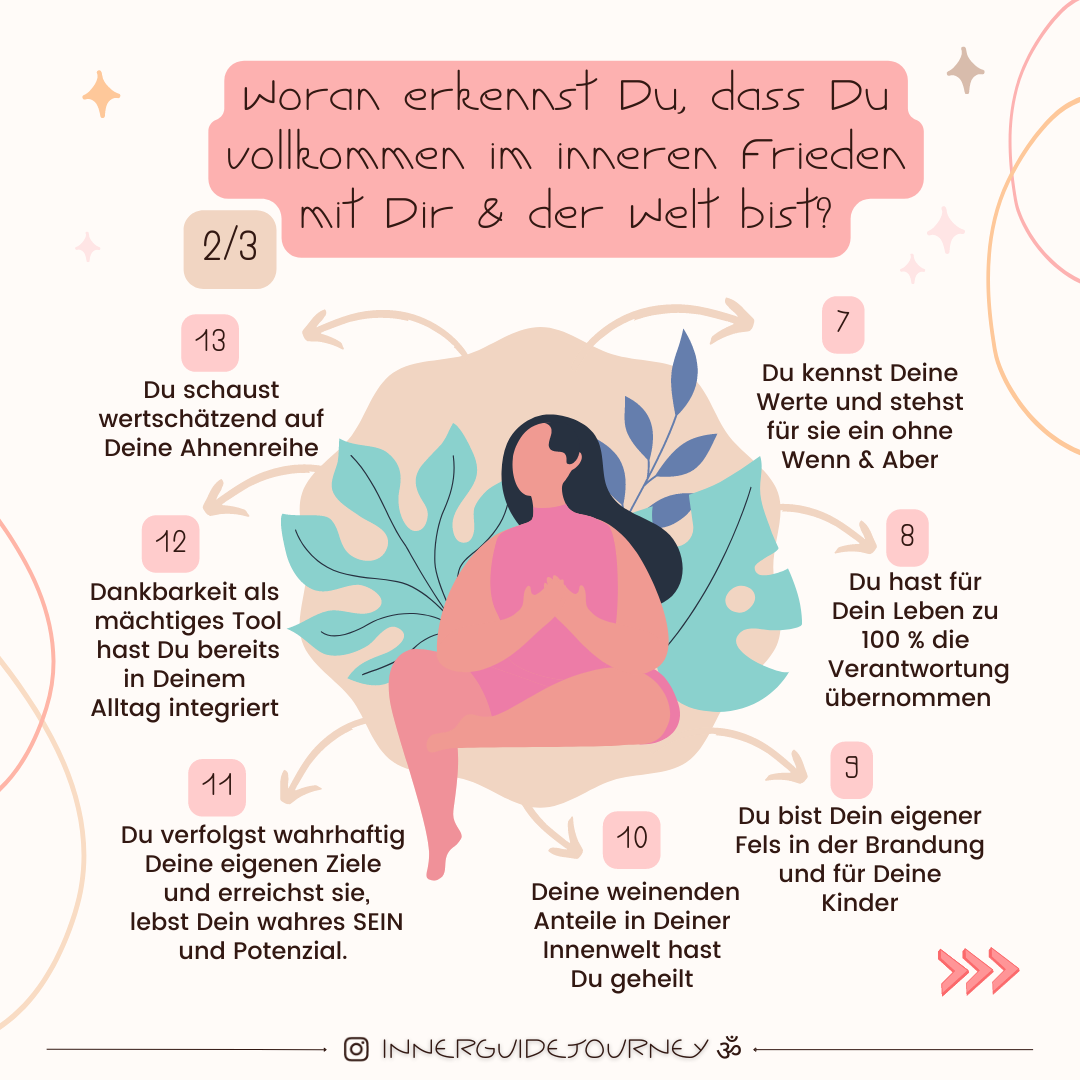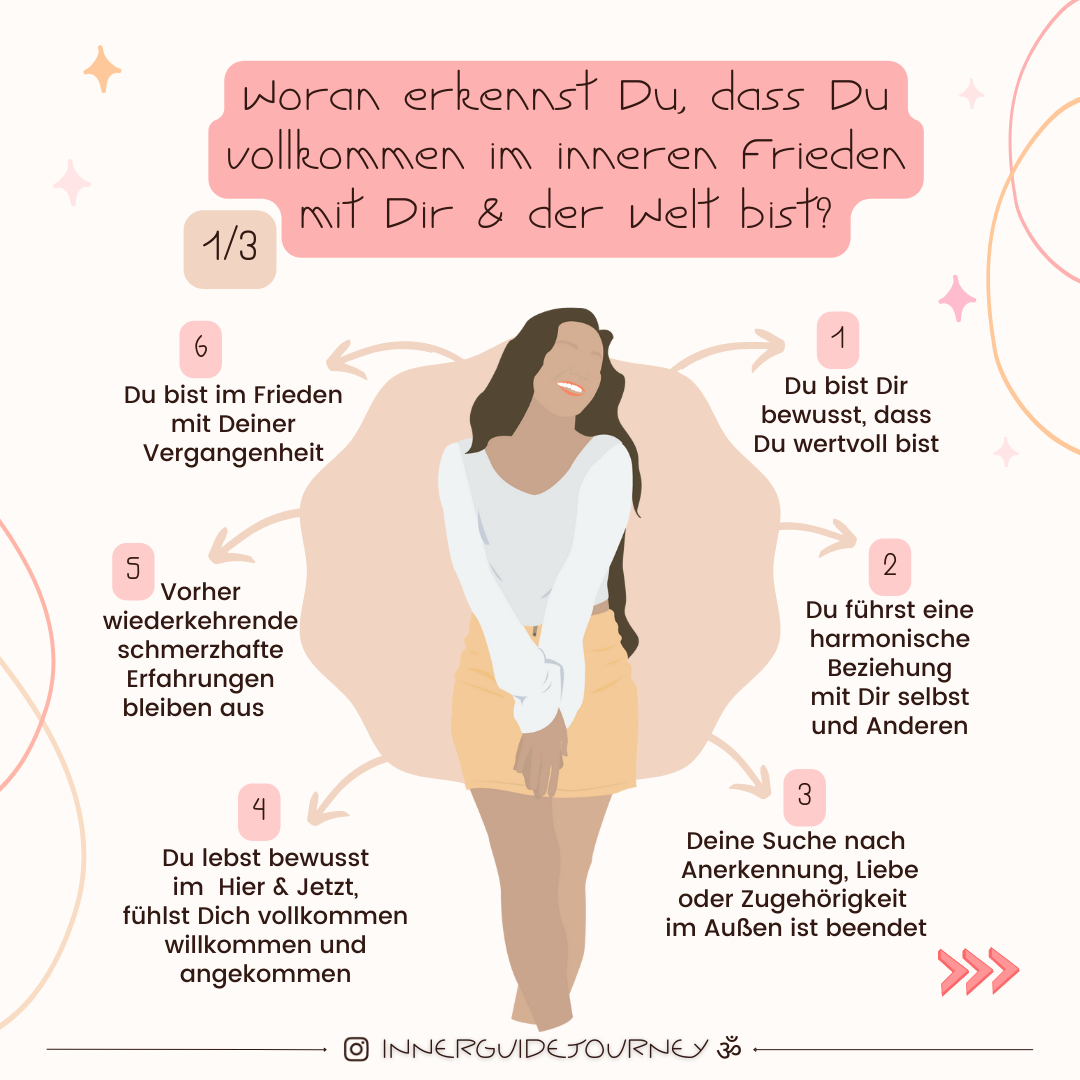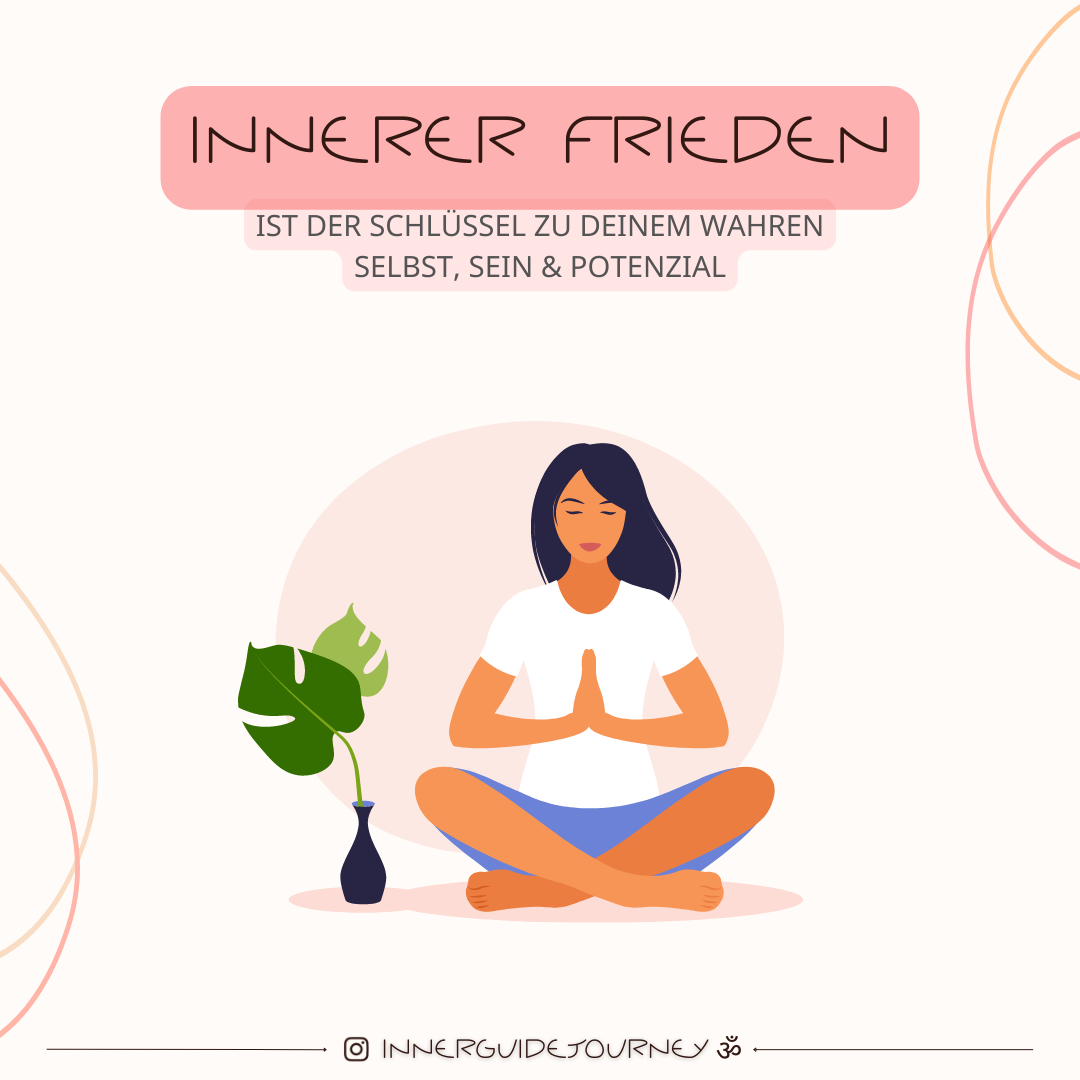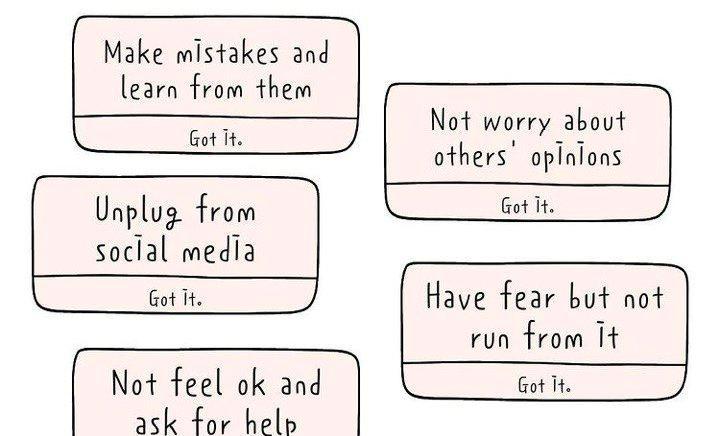
Welche Schriften für Insta-Kacheln?
Eine Frage noch:
welche Schriften als H1 und normalem Text eignen sich für Insta Kacheln. Die Schriften sollten weiblich, erwachsen, etwas reifer wirken und dennoch Pfiff, Lebendigkeit, Lebensfreude ausstrahlen. Nur nicht nervig oder aufdringlich sollte sie wirken und eben auf kleinem Raum dennoch gut lesbar sein und das frau sich beim Lesen von ihr angesprochen fühlt (losgelöst vom Inhalt).
Die beiden Schriften im Anhang finde ich nicht unsymphatisch, habe jedoch nicht herausgefunden, wie sie heißen.
Was sind Eure Vorschläge?
Diese Schrift ist symphatisch, mir jedoch für meinen Zweck zu groß und die Kugelschreibervariante für meine Designart nicht geeignet - siehe Insta Content von mir. Für meinen anderen Insta Account hingegen würde sie etwas besser passen, wobei sie mir auch da zu groß ist. Ich benötige 1 - 2 zusammenpassende gut lesbare Schriften für Content auf kleinem Raum. Im Moment verwende als Überschrift die "Tibet" und für den Text Poppins Medium, Lexend Deca und IreneFlorentina. Ich überlege, meinen Content zu straffen und mehr nur Text, unterstützt mit Minigrafiken zu erstellen, da das bisherige Design sehr zeitaufwendig ist.
Eine Schrift ähnlich wie oben im 2. Bild sichtbar suche ich. Weißt Du, wie diese heißt? Oder kennst Du eine ähnliche Schrift wie diese? Ich finde, sie kann im Raum gut für sich allein stehen. Die erste Schrift von Bild 1 habe ich verworfen, da sie mir doch zu verspielt ist.
Ähnlich wäre die Boho Lifestyle. Es gibt bei creativemarket hunderte bis tausende solcher und ähnlicher Fonts, da musst du dich mal bissl durchwühlen.
🙈 Comic Sans … nope. Dennoch danke für Deine Beteiligung & Zeit.
Geht mir genauso, daher „Alternativen“.
Schon mal reingeschaut? Die St Florence geht zum Beispiel in die gesuchte Richtung und ist von ziemlich guter Qualität, sowohl ästhetisch als auch im Zeichenvorrat.
Des Weitern könnte Dir die LiebeErika gefallen, auch ein Schmuckstück in diesem Genre.
Aber um ehrlich zu sein: Die Herangehensweise scheint mir bisher noch etwas unglücklich. Ich denke zunächst sollte man mal den Font zu Deinem Logo festlegen (und ruhig mit etwas Zeit, zumal ja gerade Feiertage sind). Dann eine passende Hausschrift ableiten. Und danach ggf. noch eine Schmuckschrift (wie hier gesucht), damit alles gut miteinander zusammenspielt und harmoniert. Außerdem sind mir bei Deinem Logo (Bildmarke) einige formale Ungereimtheiten aufgefallen, und Du wärst gut beraten, das in diesem Zuge mal überarbeiten zu lassen. Ja, ich würde Dir für ein so wichtiges Aushängeschild wie das Erscheinungsbild des eigenen Unternehmens sogar generell die Unterstützung eines Profis ans Herz legen um wirklich zu einem stimmigen, überzeugenden und für Deine potentiellen Kunden auch attraktiven Ergebnis zu finden. Aber das ist natürlich Deine Entscheidung. 🙂
🙏🏻 Danke. Sind beides sehr auf mich freundlich wirkende Schriften. Gut passend für Schulmaterialien. Das Langgezogene & Starre finde ich für meinen Einsatz nicht so stimmig. Die Schrift darf lebendiger sein, wie unser Leben - ohne das sie nervig oder aufdringlich ist. Und nicht zu arg rundlich.